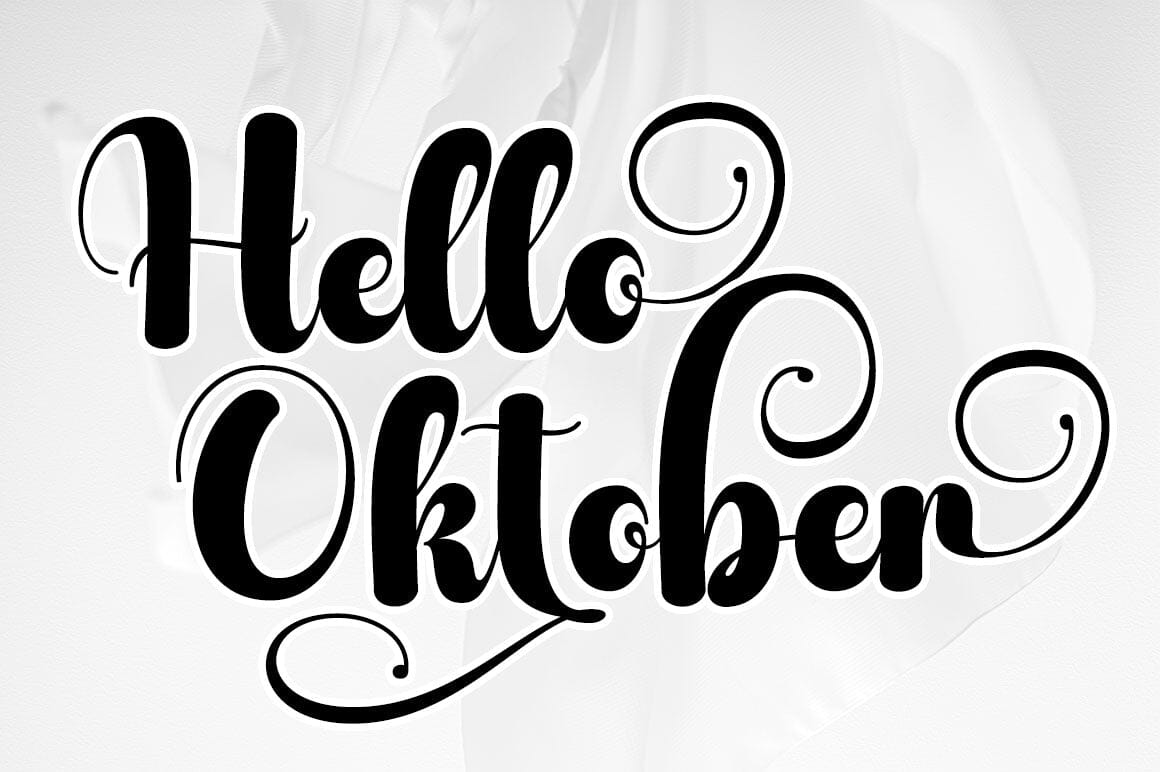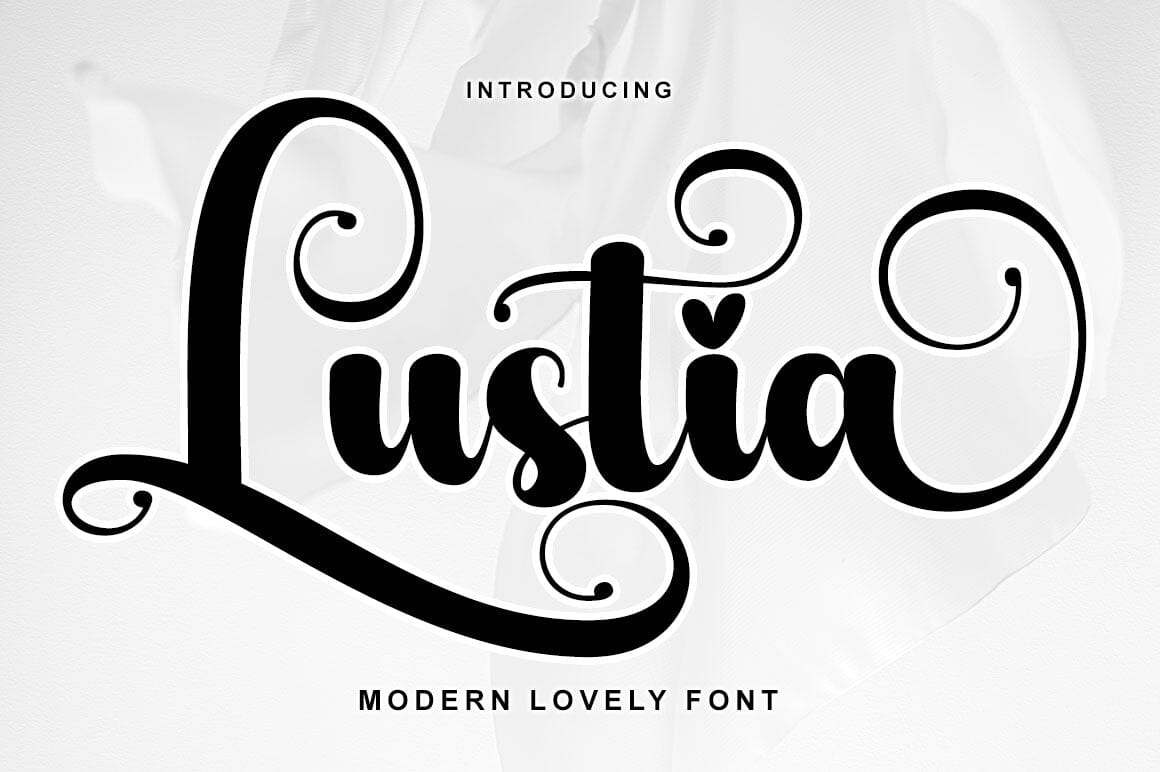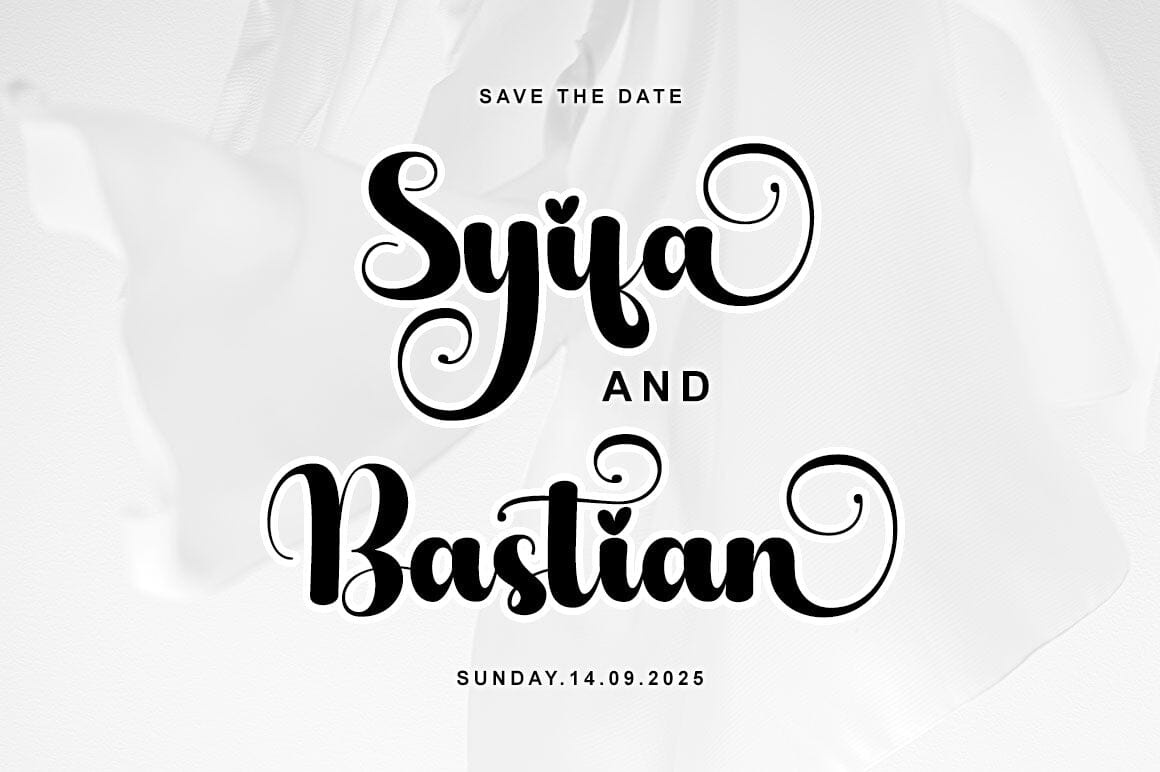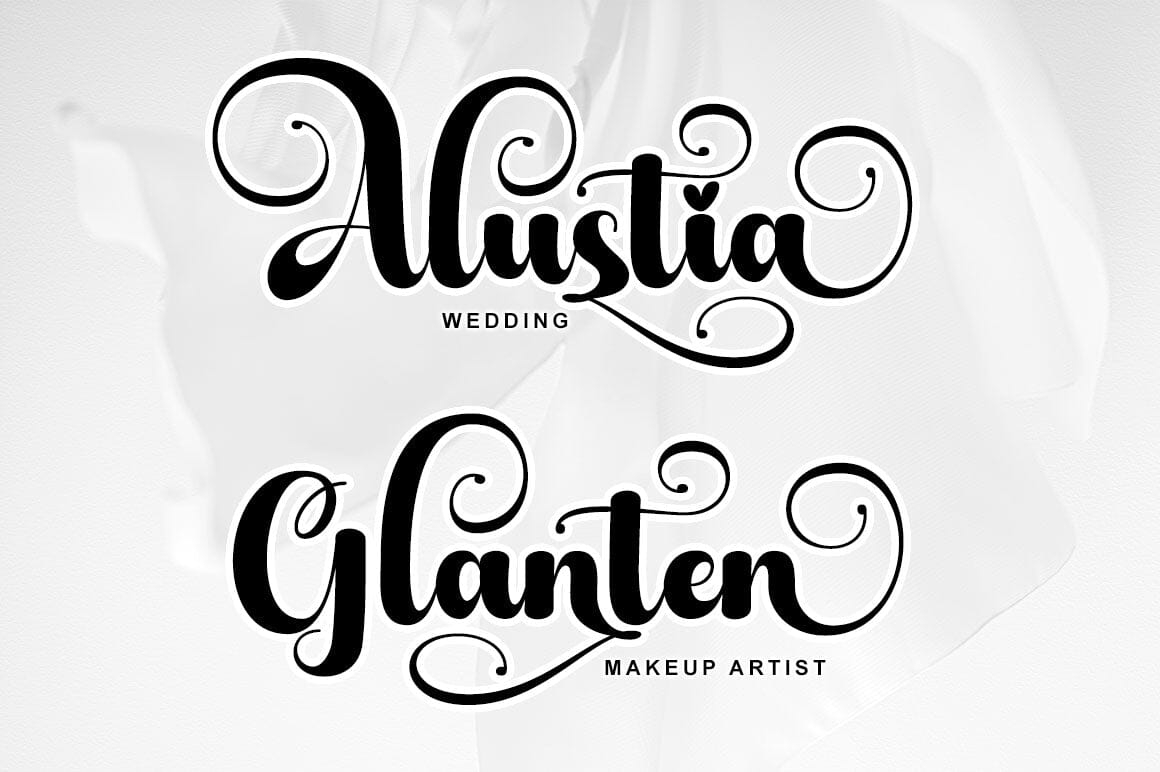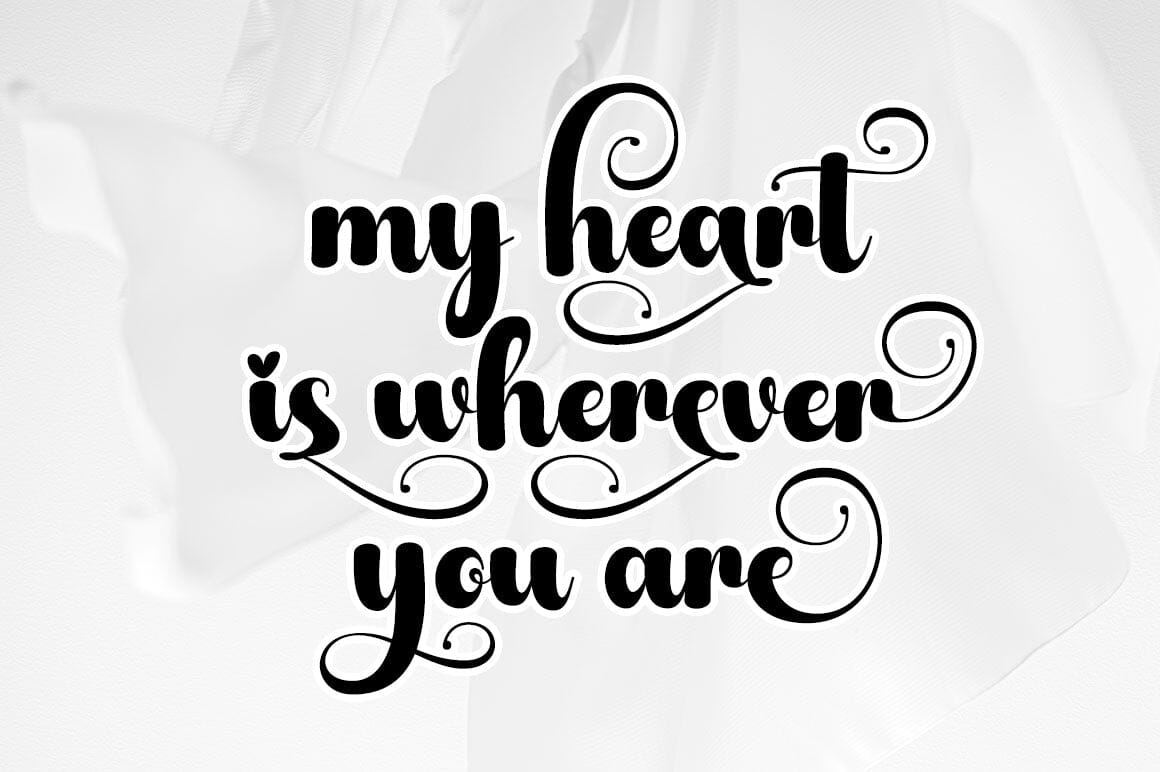
About Lustia Script
Lustia Script adalah font tulisan tangan yang elegan dan mengalir. Ini berkode PUA yang berarti Anda dapat mengakses semua mesin terbang dan swash dengan mudah! Ini menampilkan garis dasar yang bervariasi, garis halus, mesin terbang yang indah, dan alternatif yang menakjubkan. Ini mempertahankan pengaruh kaligrafi berkelas sekaligus terasa kontemporer dan segar. Jatuh cinta dengan font ini dan bawa proyek Anda ke level tertinggi!